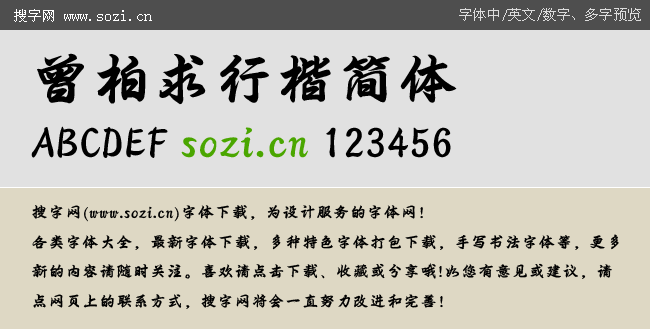
方正字跡-曾柏求行楷簡體
搜字網(wǎng)給大家提供一款方正字跡-曾柏求行楷簡體中文字體下載。方正字跡-曾柏求行楷簡體是一款非常漂亮的行楷字體,字形流暢大方,效果十分漂亮。此款字體適用于包裝設(shè)計(jì)、廣告設(shè)計(jì)、海報(bào)設(shè)計(jì)等視覺環(huán)境。
• 風(fēng)格類別: 行楷